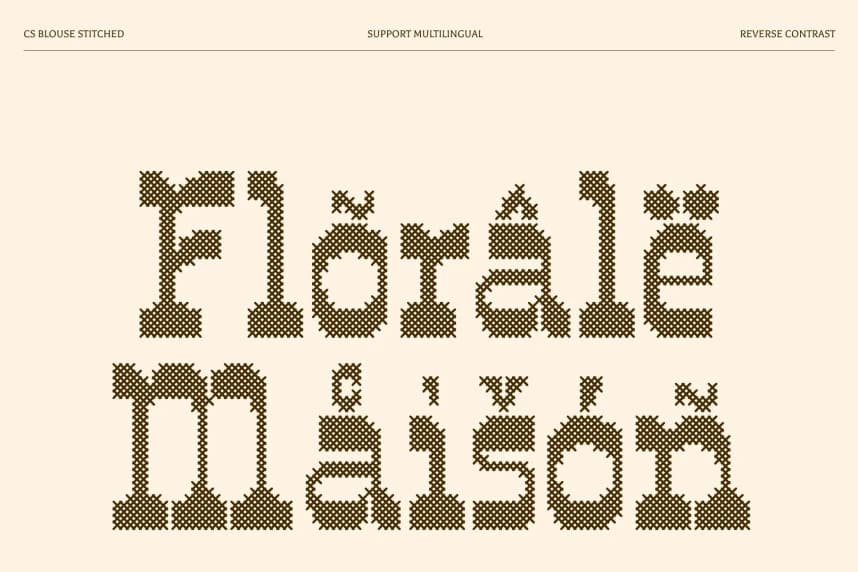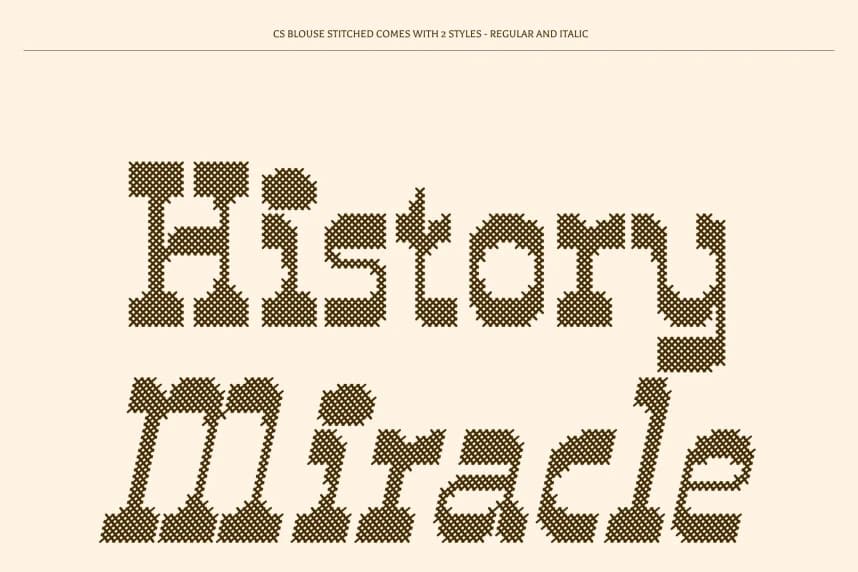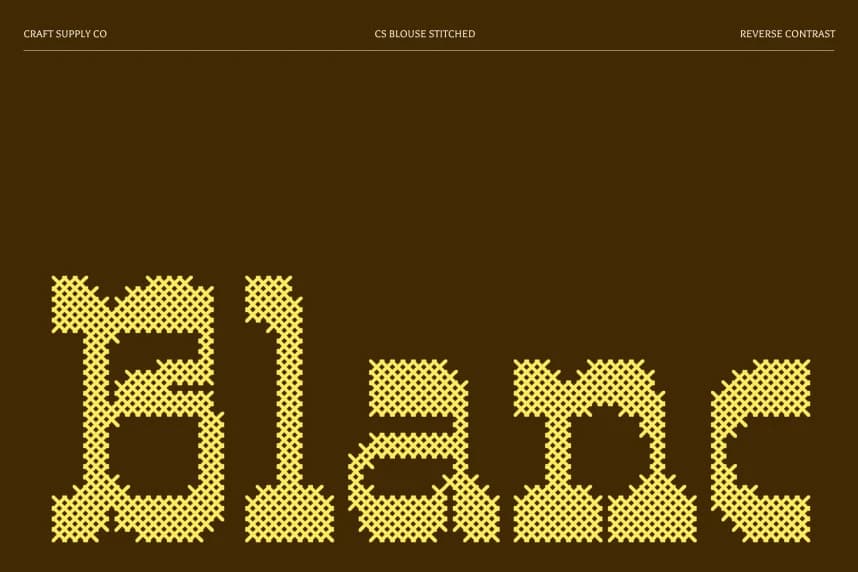
CS Bluz Dikişli Yazı Tipi
CS Blouse Stitched Font – El Yapımı Doku ile Kalın Ters Kontrast Serif, Ters Kontrast ile Alışılmadık Zarafet. Bu, ters kontrastın kendine özgü güzelliğini kucaklayan bir gösteri serif yazı tipidir.
CS Blouse Stitched Font – El yapımı dokuya sahip cesur bir ters kontrastlı serif; ters kontrastla gelen alışılmadık zarafet. Bu, ters kontrastın kendine özgü güzelliğini kucaklayan bir gösteri serif yazı tipidir